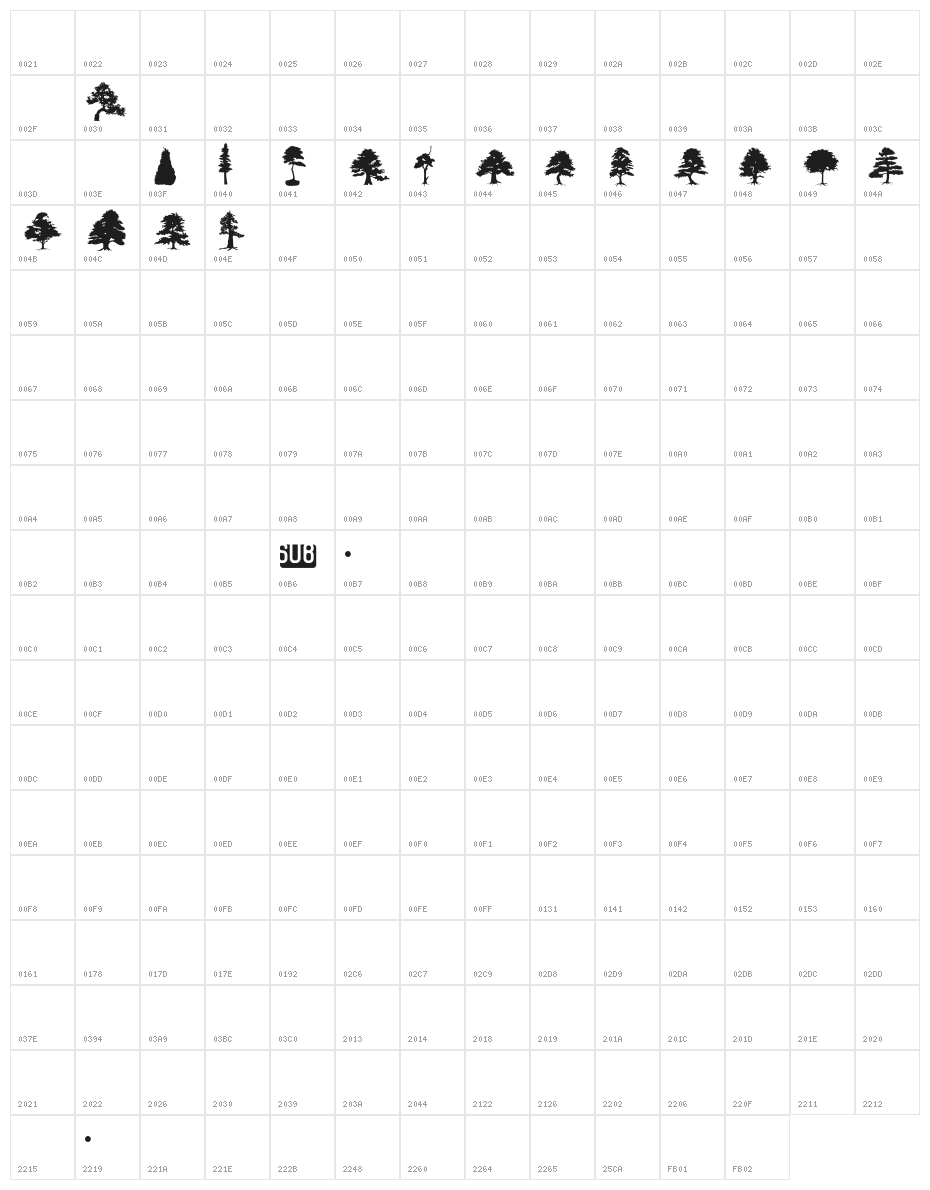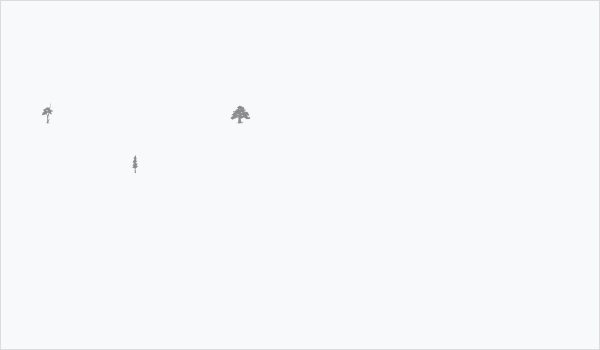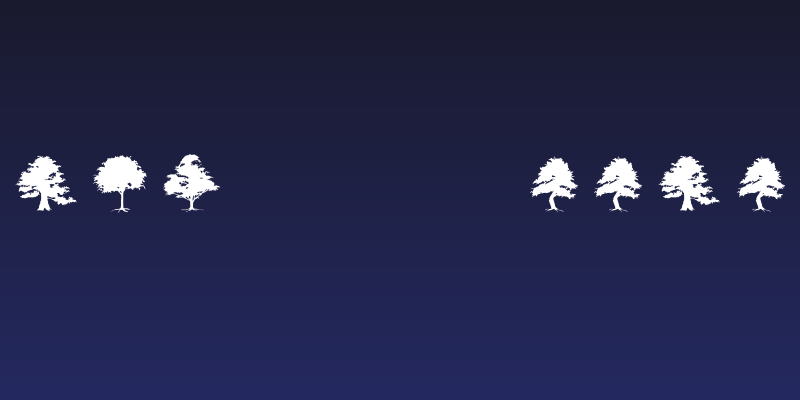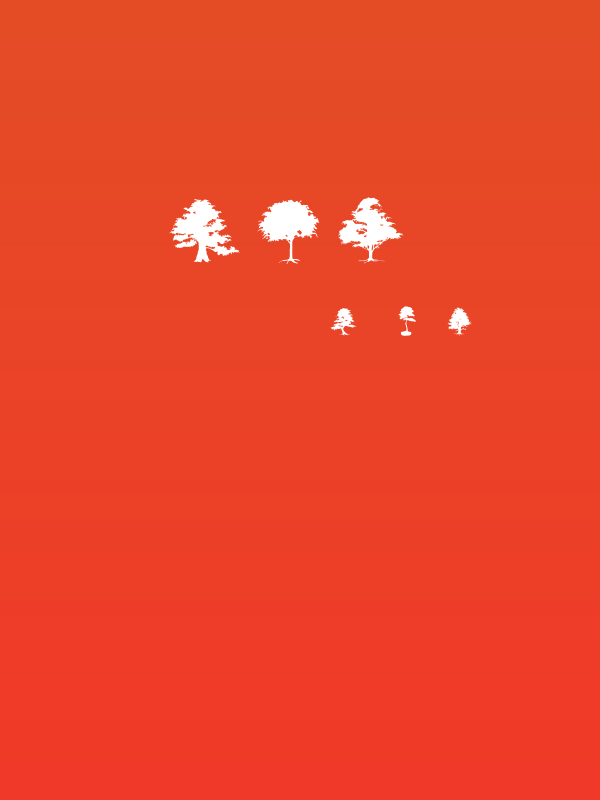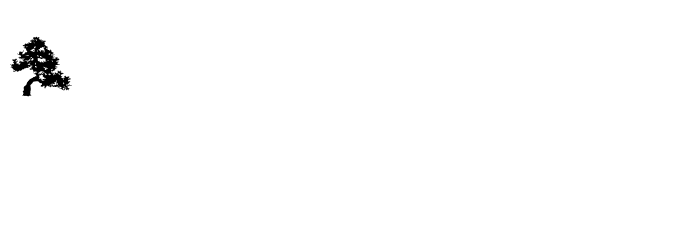
SubiktoTreebeta Font
| Gesamtstil | Decorative, Organic, Nature-inspired |
| Anwendungsfall | Logos, Headlines, Posters, Themed graphics |
| Vorgeschlagene Projekte | Nature-themed posters, environmental branding, eco-friendly packaging, educational materials, children’s books, event invitations. |